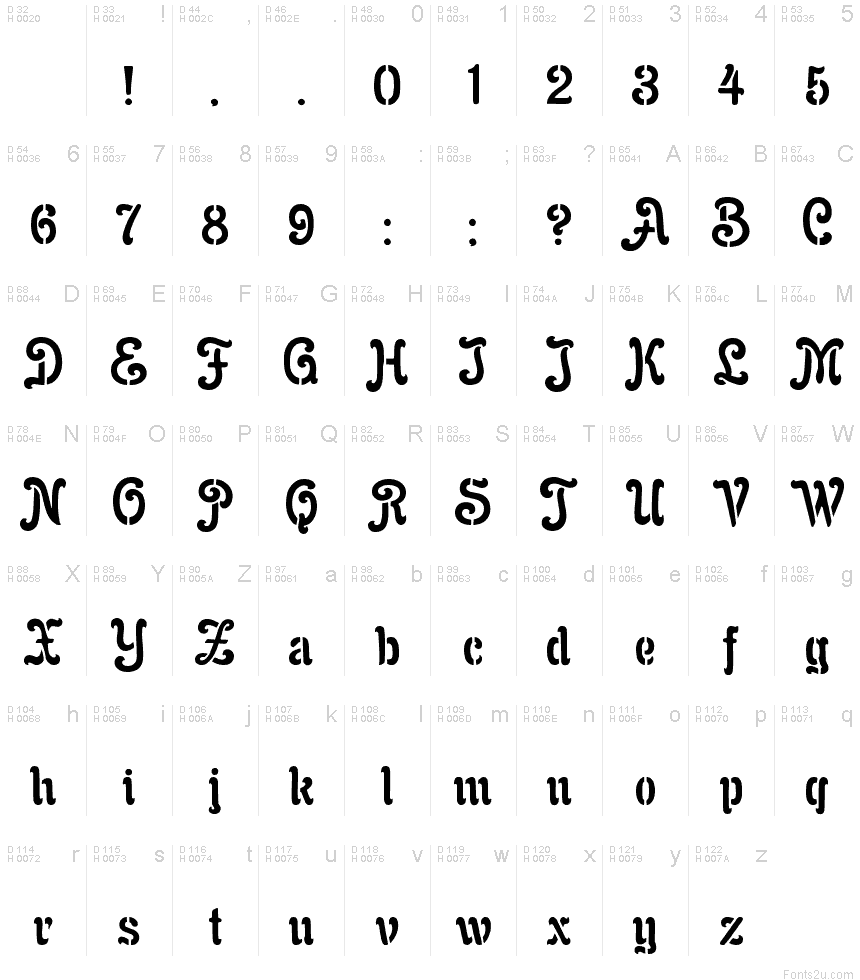
Shamcil, darmowy, zakręcony krój typu display od Shamrocking i king-o-type z 2000 roku, stawia na zabawny, retro klimat dzięki grubym, miękkim literom i ciasnym loczkom wplecionym w ich formy. Zaokrąglona waga nadaje mu przyjazny charakter, a przycięte otwory i wyolbrzymione łuki nadają słowom żywy, „zabawkowy” rytm, niczym z dawnych plakatów.
Sprawdzi się wszędzie tam, gdzie tytuł potrzebuje uroku, a nie powściągliwości – szyldy butików, okładki książek dla dzieci, opakowania słodyczy czy pieczywa, zaproszenia na imprezy oraz krótkie logotypy to idealne zastosowania dla tego darmowego fontu. Wykorzystaj go do krótkich nagłówków lub dużej inicjały, jeśli chcesz, by to jego pękate krzywizny i zakręcone detale grały główną rolę.